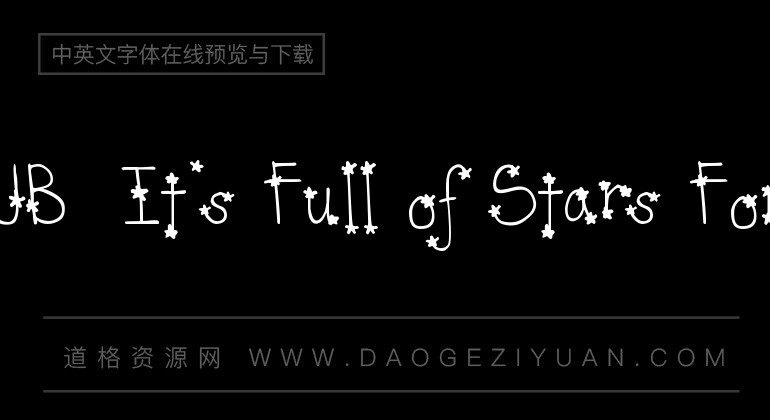
DJB It's Full of Stars Font 是一种手写字体,由字体设计师 Darcy Baldwin 设计。这种字体非常适合用于手写信件,日记,或其他需要一种个性化、温暖的字体的场合。 该字体具有特点的不规则形状,以及手写风格的特征。字母之间的间距较小,使得整个字体看起来更加连贯和自然。此外,DJB It's Full of Stars Font 还包括了一些特殊字符和符号,如心形图案、星星符号等,这些符号使得这种字体更加具有个性和创意。内容介绍
DJB It's Full of Stars Font是一款非常不错的手写艺术字体,具有很好的视觉感,适合于文化类的宣传设计、商业类品牌的广告和产品包装设计以及个性化文字排版等较多场景。